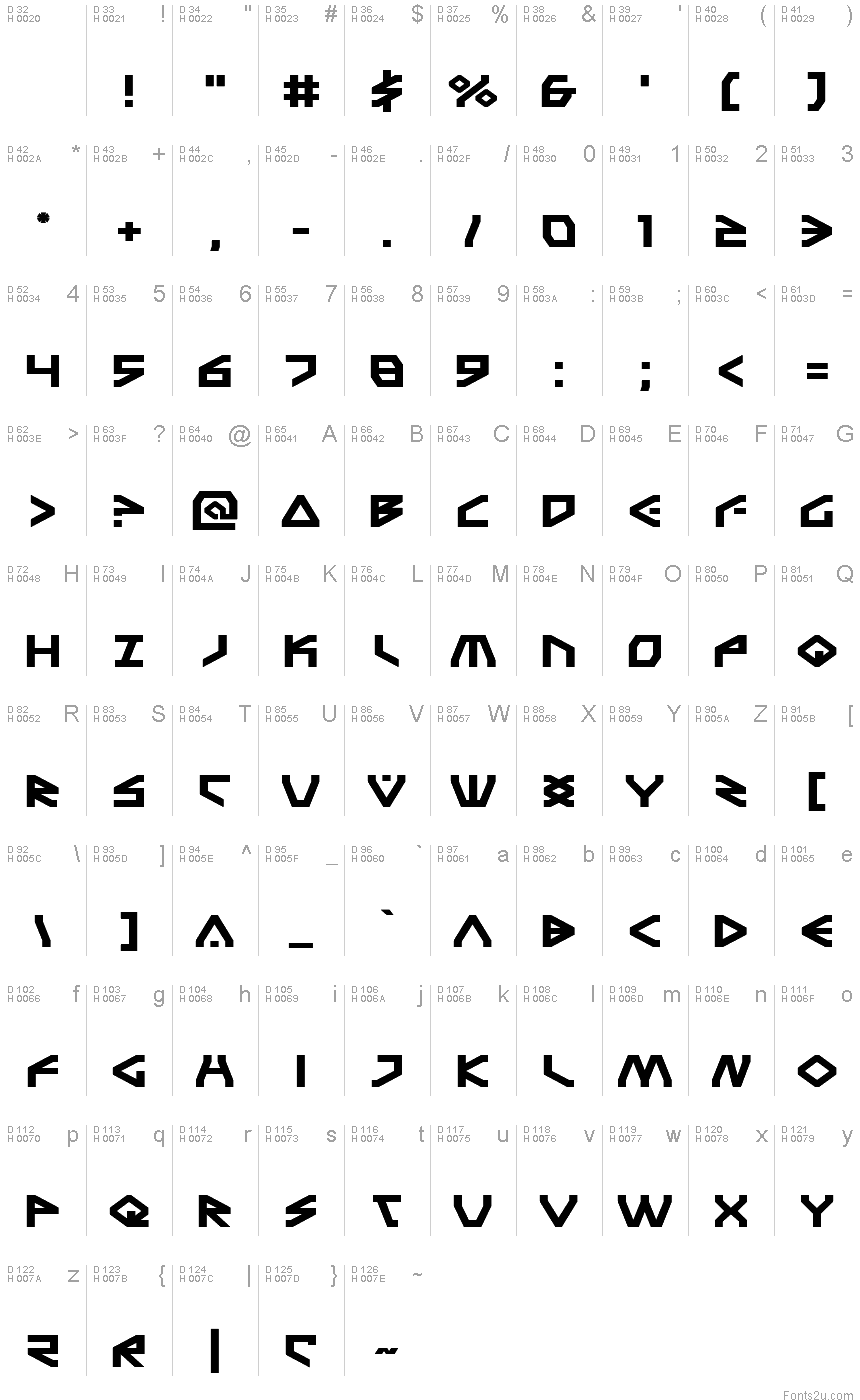
Terra Firma Expanded
Terra Firma Expanded von Iconian Fonts ist eine kostenlose, kantige Techno-Display-Schrift mit hart geschnittenen Großbuchstaben und einem scharfen, technischen Rhythmus. Die Buchstaben setzen auf abgeschrägte Ecken, dreieckige Verbindungen und offene geometrische Zwischenräume, die eher an Beschilderungen aus einem Sci-Fi-Korridor erinnern als an eine gewöhnliche Headline-Schrift.
Sie eignet sich perfekt für Spiele-Logos, Plakat-Titel, Albumcover, Einblendungen und Tech-Event-Branding, bei denen eine kostenlose Schrift einen strengen, maschinellen Look benötigt. Verwenden Sie sie für kurze Überschriften, Monogramme und Cover-Texte, wenn die Großbuchstaben in einer breiten, architektonischen Silhouette ineinandergreifen sollen.